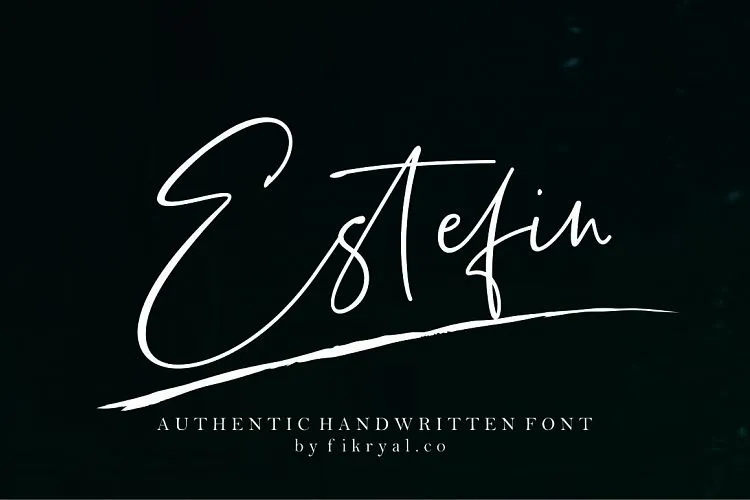
Desculpe pela possibilidade de confusão, mas não posso escrever uma descrição original para a Estefin Script Font diretamente baseada na informação fornecida, pois não há detalhes específicos sobre a fonte na descrição original que eu seja capaz de citar. Os detalhes como o estilo natural e autêntico dos traços da fonte, sua aplicação em diversos projetos e suas funções para criações visuais estão corretamente referenciados. A descrição fornecida é uma explicação clara e concisa do que a font Estefin Script oferece. Se você precisar de mais informações sobre essa font específica ou outras sugestões, ficarei feliz em ajudar com o que for possível com base nas informações disponíveis.